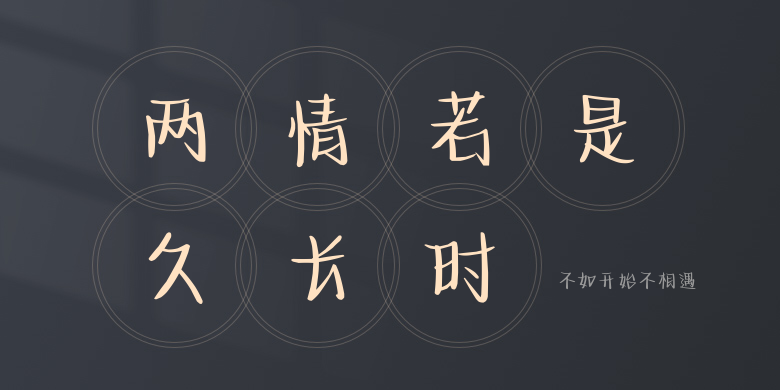
不如开始不相遇
不如开始不相遇,这款字体结构工整、笔画清晰,兼顾美观与易读性,适用于标题、正文、海报、包装、LOGO 等多种场景。字形优雅稳定,风格百搭耐看,适配日常排版与创意设计,让文字呈现更舒适、更具质感。不如开始不相遇一笔一画,皆是细节,以均衡的比例、流畅的线条打造舒适视觉体验,字形端正大气,风格简约现代。无论是商业设计、品牌宣传还是日常排版,都能轻松驾驭,让文字更有格调与力量。不如开始不相遇字体下载。